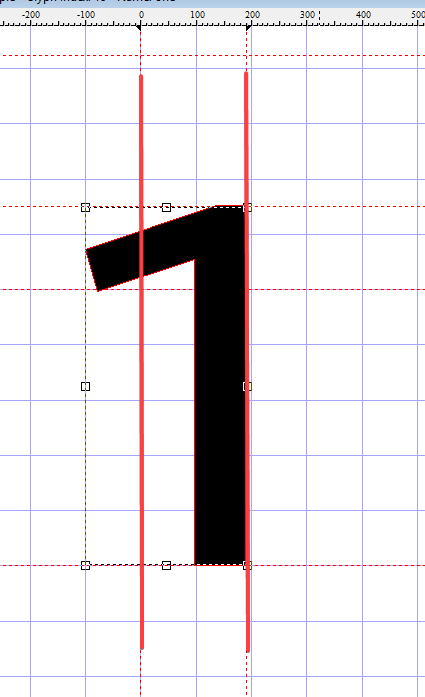
Wie optischen Hauptkörper ermitteln?
Hallo Freunde der Kunst! Wie bekommt man den optischen „Mittelkörper“ (oder wie man's auch nennen mag) einer Glyphe heraus? Ich möchte ein paar Lettern in Adobe Illustrator genau mittig setzen, aber halt optisch mittig, und nun frage ich mich, wo ich die bearings rechts und links setzen muss. Ob man das nach Gefühl macht, oder ob es dabei Richtlinien oder Grundsätze gibt, die einem helfen können vom bloßen Bauchgefühl wegzukommen? Als Beispiel nehme ich mal die Ziffer 1 als typischen Problembären. Wo das rechte bearing sitzen soll ist ja offensichtlich, aber bei dem linken bearing bin ich mir nicht sicher? Mein Bauchgefühl verlässt mich ...
Mir geht es wohlgemerkt nicht um Fließtext, wo die bearings den Abstand zum nächsten Buchstaben festlegen. Sondern um Lettern die ganz allein und harmonisch-ausgewogen im horizontalen Zentrum eines Rechtecks sitzen sollen.
Vorweg: keine Ahnung. Zweiter Gedanke: Hast du eine Testdatei? In dieser könntest du die Ziffern zufällig verteilt in Rechtecken horizontal und vertikal anordnen, drehen und spiegeln. Ich denke, dann würde man merken, wer aus der Reihe tanzt?
:-?Wenn es optisch passen soll, geht es nur nach Gefühl – aber eben nach dem Augengefühl statt nach Bauchgefühl ;-)
Drehen und Spiegeln ist oft ein guter Trick um das Auge zu überlisten, hilft aber nicht unbedingt, wenn es denn nachher richtigrum richtig aussehen soll … da hilft manchmal nur Gefühl und Wellenschlag.
Ich würde hier vom fertigen Text eine Screenshot machen, und da recht kräftig einen Gaußschen Weichzeichner drüber ballern, sodass nur noch eine Art Schatten übrig bleibt, da sollte man dann recht gut erkennen, welcher Schatten nicht ganz richtig steht. Für mich als träger einer recht starken brille habe ich den Weichzeichner ja immer dabei, einfach über die Brille peilen. So hat das dann doch was praktisches...
catfonts, was den Schatten angeht, ist das sicher ne gute Idee, ich habe bisher immer ganz weit rausgezoomt, bis nur noch ein Pixelknubbel erkennbar war, dann läßt sich das Auge auch nicht so sehr von Ausläufern, Nasen, Füßen, und allem was nicht zum gefühlten Mittelkörper gehört, ablenken.
Ich meine ein Prinzip für die Ziffer 1, wie auch für die Letter J, gefunden zu haben. Und zwar, wenn man den  Ausläufer vom Hauptbalken (‹Nase›, beim J der ‹Schweif›) gedanklich als separate Masse betrachtet, und ihn auf einem Finger balanciert. Dort wo der Massenmittelpunkt liegt, könnte das bearing sitzen. Deckt sich das mit Eurer Einschätzung? Bei andern Lettern, ist es wiederum anders. Z. B. bei der Letter Q sind die optisch-harmonischen bearings wohl eher die gleichen wie bei der Letter O, d. h. man tut so als existiere das kleine Schwänzchen vom Q gar nicht. Oder, weiteres Beispiel, bei der Letter L ist der Querschenkel unten viel zu dominant um gemittelt werden zu dürfen. Er darf wohl allenfalls minimal angeschnitten werden ( oder vielmehr gar nicht? ). Letztlich habe ich keine Universal-Regel, sondern für ca. 5-10 Formtypen jeweils ein Analogprinzip, das ich übertragend anwende. Immerhin.
Du könntest Dir dazu auch nochmal andere hochwertige Fontfamilien anschauen um zu sehen wie man da mit solchen Dingen umgegangen ist. Die Thesis-Sippe von Luc(as) de Grot zum Beispiel ist meiner Ansicht nach eine sehr gute Referenz. Oder eine Open-Source-Schrift wie die Fira, Noto oder IBM Plex, wenn Du Infos »hinter den Kulissen« benötigst.
Robert, naja, die Schwierigkeit ist, daß in normalen Schriftfamilien die bearings nach dem Kriterium "Fließtext" gesetzt sind, nicht nach meinem Kriterium "singulär-stehende Lettern". Ich weiß nicht ob ich da Informationen zum optischen Mittelkörper rausziehen kann..
Ich bin davon ausgegangen, dass man diese ja auch zentriert setzen können und es dabei optisch funktionieren muss. Und über die DTP-Software könnte man ja optional auch noch einiges steuern  – Stichwort optischer Randausgleich.
Hast Du das mal probiert: relevante  Einzelzeichen einer »Vorbildschrift« zentriert gesetzt und ggf. unter Deine Zeichen gelegt?
Das ist ein guter Hinweis, ich werde es in Adobe Illustrator mal testen.